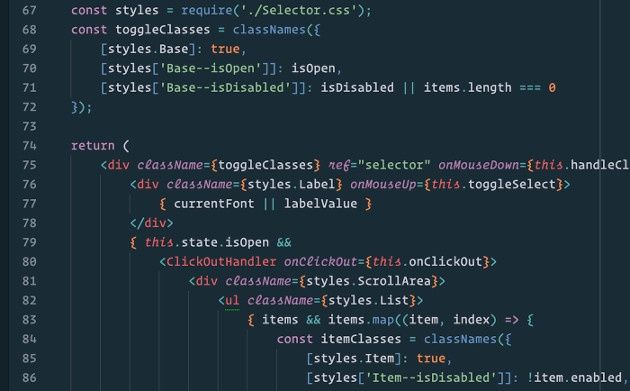
Operator Mono: font, który ma ułatwić programowanie
Czy dobry font jest w stanie usprawnić pracę programiście? Firma Hoefler & Co. uważa, że jak najbardziej.
Operator Mono
Hoefler & Co. – jedna z najbardziej cenionych firm typograficznych – opracowała nowy font, stworzony z myślą o programistach. Operator Mono, bo tak się nazywa, został podobno zaprojektowany w taki sposób, by maksymalnie ułatwić życie tym, którzy tworzą strony i aplikacje, z których wszyscy korzystamy.
„Przy projektowaniu Operatora pogłębialiśmy naszą wiedzę na temat języków Javascript i CSS” - powiedział założyciel firmy, Jonathan Hoefler. Dzięki temu podobno font wyraźnie akcentuje i odpowiednio rozmieszcza nawiasy, przecinki, średniki oraz inne często używane znaki. Chodziło też o to, by różnica pomiędzy takimi znakami jak „I”, „l” i „1” była widoczna na pierwszy rzut oka.
Oprócz samego kroju Operator Mono osiąga swoje cele również dzięki zastosowaniu akcentów kolorystycznych oraz kursywy (ścisła współpraca z narzędziem Atom). Dla przeciętnego użytkownika może to wydawać się chaotyczne, ale programiści powinni być zadowoleni. Pytanie tylko, czy wystarczająco rozentuzjazmowani, by wydać na font 200 dolarów…